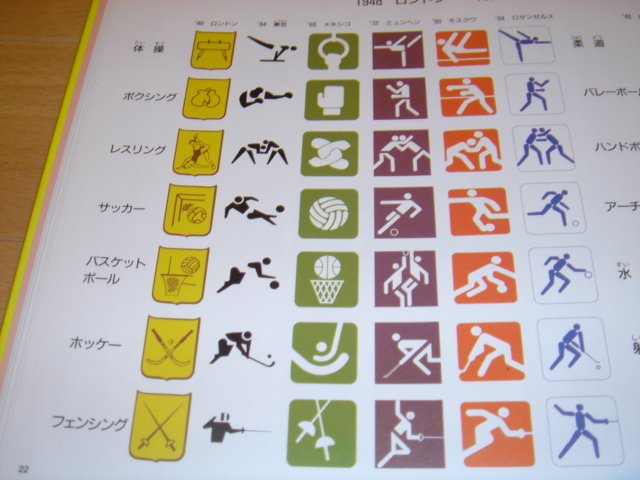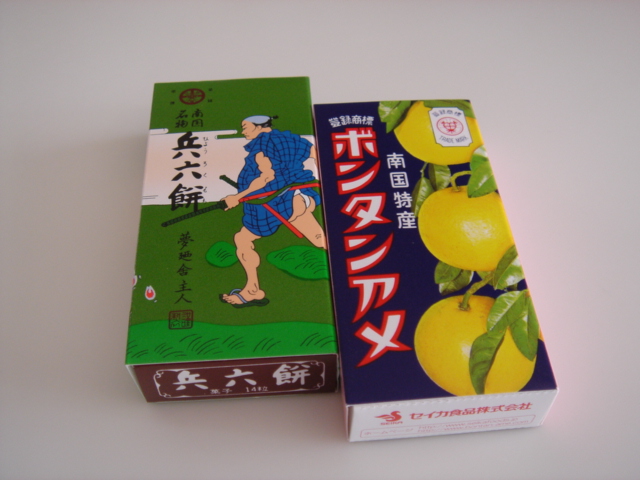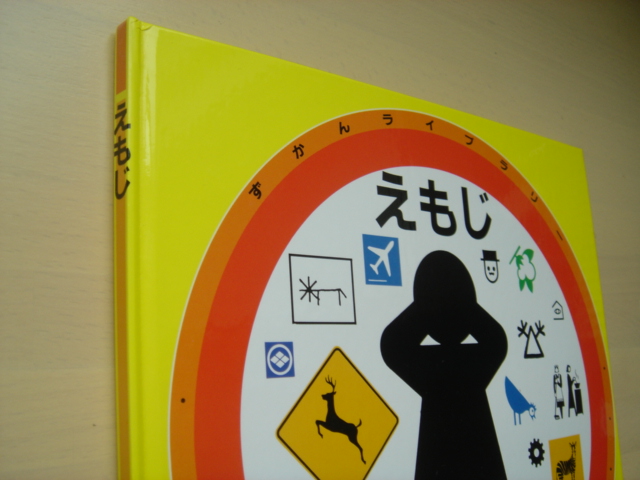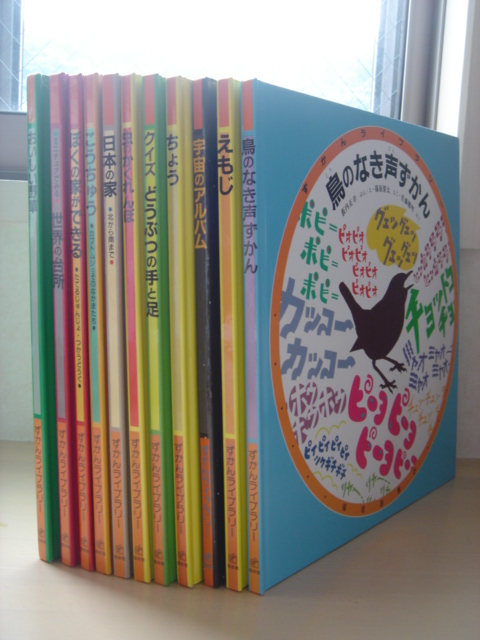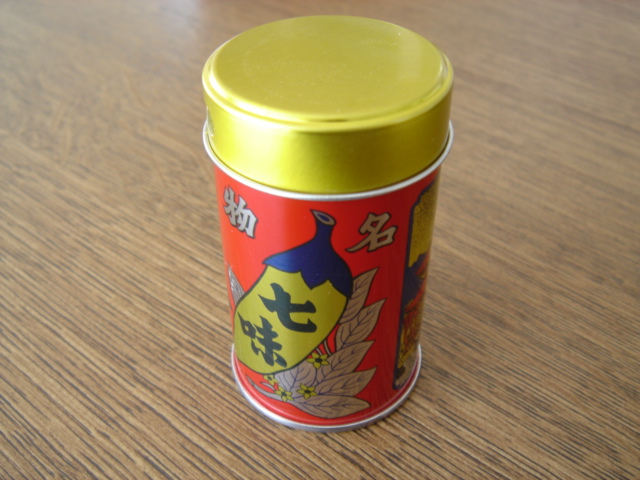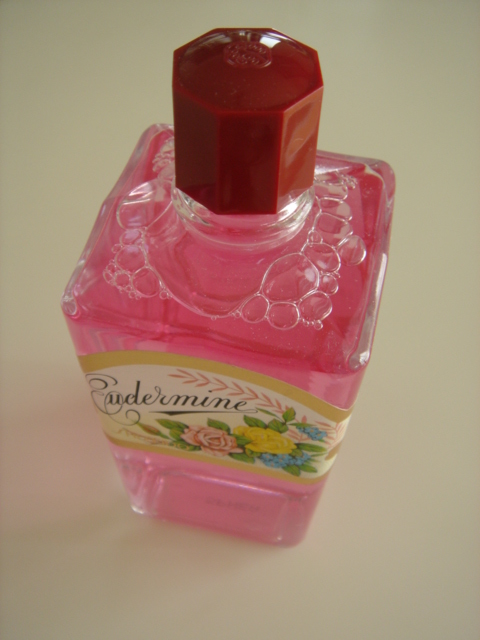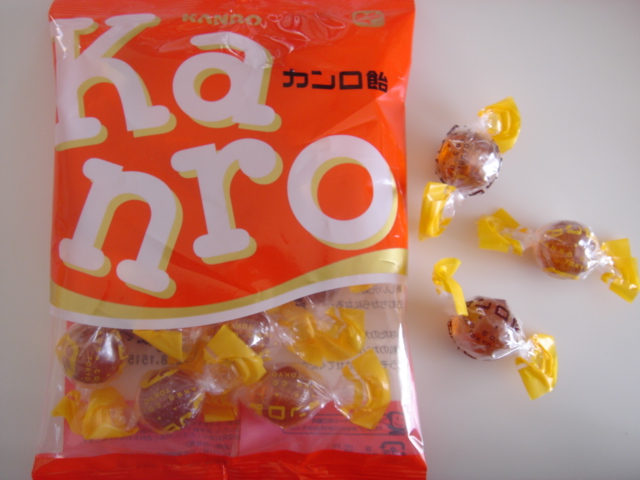
昔なつかしパッケージ
近所にドラッグストアがあるので、いざというとき便利です。
なぜかお菓子を買うことが多いですが…(どうでもいい「いざ」ですね)
先日ぶらぶらと棚を見ていたら、これを、発見!
なつかし〜。母の鏡台にあったわ〜。ピンク色の化粧水。
オイデルミン、ああ、そんな名前だったかも。
と、手にとったらかわいいラベルとレトロなビンの形に目がくぎづけ!
ところでこれ、なんですか?ははあ、ふき取り化粧水ですか。
もう、いかにも色つけました、というピンク色で、ああ〜かわいいっ!
昔から変らないものってなんてすてきなんでしょう。
置いておくだけでも幸せ感がたっぷりです。特にフタの形がいいです。
使ってみたところ、香りにビックリですが、使用感はなかなかよかったですよ。
お菓子も昔からあるものはパッケージも魅力的ですよね。
森永のキャラメルや明治のサイコロキャラメル、好きですねえ。
このボンタンアメは駅の売店などにもあるような…この箱も昔から
変らないですね。
左の兵六餅はご存知?
抹茶ふうな味の(食感はボンタンアメと同じ)素朴なお菓子です。
九州人はよく食べるのかなあ。子どものころからのおなじみの味です。
ミルク系の飴がのどにいい、と信じている私ですが
ここのところのメラミン騒ぎで、ちょっと敬遠しております。
スースーしないタイプで、のどによさそうな飴はないかしら?
すると目に付いたのが「カンロ飴」、まだあるんですね!
このねじってあるタイプの飴は最近見かけないですから貴重。
なつかしい味です。噛みにくいから長持ちしますね、変なところに感動。
これもお気に入り!
先週信州小旅行に行ったとき、お昼は二回ともお蕎麦屋さんへ。
どっちのお店にも置いてあったのがこの七味でした。
容器のデザインに惹かれて即買いです。
かわいいなあ。
食卓でもにんまりしてます。
えもじ
調べたいことがあって、ふと思い出した子ども用の図鑑です…
絵本のような図鑑のような、なかなかユニークなシリーズなので「あれは確か、あのページに載っていた」という記憶がはっきりしているのです。
福音館書店の「ずかんライブラリー」というものですが、書店での発売はなく幼稚園での注文販売でした。このシリーズの中に「えもじ」があります。パラパラ見ているだけで楽しい!
北京オリンピックのテレビ放送でいろいろな競技のピクトグラムを見るのはなかなか楽しかったです。パラリンピックも始まりますが同じ人がデザインしているのでしょうか。
スポーツなどの大会に限りませんが異なる言語の人々のためにシンプルに表現されているのは、本当に見事。
で、この「えもじ」の中にもオリンピック競技のものがありました。
1948年のロンドンオリンピックでは、ボールなど競技に使う物や道具をデザインしたものが多かったんですね。その後は「人」中心のデザインに変わっているんだ〜。
私は東京オリンピックの時のものが好き。とても洗練されていると思います。
8年後に東京でやるなら、またこれを採用するなんてことは…ないのかな。
街中や公共の施設では欠かせない絵文字。非常口のサインはやっぱり目立ちますねえ。一番お世話になっているのはやっぱりトイレ…?
男女を青と赤で区別しているのは日本や韓国だけのようなのですが、これに慣れているせいか、たまに男女とも黒で(オシャレに!)表示されていたりすると「あれ、どっちかな?」とまじまじと見てしまいます。
先日出かけたレストランでのできごと。
うちの小学生(男子)が「男のトイレがない」と席に戻ってきました。「どうしよう!」と焦っているので、一緒に行ってみると
確かに女子トイレのサインはついているけれど、男子のほうはプレートがはがれてしまったのかドアに何も表示がありません。
「片方が女子用なのだから、このドアのほうで大丈夫」と言うと「ほんとにだいじょうぶ?」とおそるおそるドアを開けていました。
自信を持って行動するためにも絵文字は大事で〜す。
美篶堂のbookstand
前に美篶堂さんでゲットしたbookstandで、一度ご紹介は
したのです…。
でもそのときは地面に立てて…。
しかし、このbookstandは、壁面にも掛けられる
優れものです。
壁にピンをで二か所とめて、そこにチェーンを
掛けます。
ちょっと恐かったら、両面テープを少し貼っても…。
姿がいいですよねぇ〜。
受け板部分が少し斜めになっているので、
カードを立てても落ちたりしません。
姿がいいでしょう〜。
ある程度の重いものも、大丈夫みたいです。
これなら文庫本とか小さなノートとか
フレーム入りの写真とか飾れます。
美篶堂の提供するもの、空間は、私の憧れです。
もう一個買おうかなぁ〜。
アルファベットのハンカチーフ
おしゃれな人からの贈り物…刺繍の美しいハンカチです。
とっても薄い綿ローン地に繊細な手刺繍で、葉っぱのところは裏側に糸がわたっているので表面はぷっくりと見える…アップリケをしたみたいな。
一枚の布として見ても、ハンカチって魅力的ですよね。
最近こんな優美なハンカチを使うことが少なくなりました。手を拭くのにはタオル素材のハンカチを使っているためです。
タオルハンカチはそれなりにかわいく、しかも実用的。だけど、日々美しいものを身の回りに置いて、見たり、使ったりも大事ですよねえ。
涙をそっと押さえたり、とか?美女なら持っているだけで
絵になります。
さて、文字入りのハンカチは引き出しにあったはず…ありました〜
華やか!周囲全部ローマンキャピタルですから!プロポーションをしっかりお勉強、って感じですかね。
パロマ・ピカソの名前入ってる…あ、だから四隅は「P」なのね。
中央の地模様も全部アルファベット。ごちそうさま〜
こういうハンカチってデザイナー本人がデザインしているのでしょうか?
絹と綿が半々のスベスベの手ざわり。周りの切り文字っぽいデザインがおもしろい。
中央部分の字はあまり好きではないけれど…「KとL」が金色になっているのは、カール・ラガーフェルドだから、か。イニシャルが隣り同士というのは、こんなふうに遊べるのですね、いいなあ。
久しぶりに出してみて思ったこと。もったいなくて使えない、よりも使って楽しいほうがいいかも。
粋な手拭い
今や手拭い専門店もある今日
この頃。
軽くてコンパクトで…。
今回は、また面白いデザインを見つけました。そのタイトルも「NIPPON」とな。
シンプルな図案がいいですね。見ながら説明できたら話しも盛り上がることでしょう〜。
でもTEMPURAはツェッペリンに見えなくないかも?
こちらは「手影絵手本」とな。
ぁあ〜、懐かしい!
子供の頃は遊びましたねぇ〜。
おばあちゃんに教えてもらいました。幼稚園でもやったような…。
海外では、どんな手影絵があるのでしょうねぇ〜?
鳴き声の違いとかすると面白いかもしれませんね…。
太陽の光が透明で強い1月あたりが撮影には
良いかと…。
風と戦いながら〜。
貼りまぜ屏風
昨年の夏の話です。
九州のとある民家に泊めてもらった日、そこの女主人にその家の家宝を見せてもらいました。貼り交ぜ屏風1双です。
貼り交ぜ屏風とは、色紙・短冊・書簡等をとりまぜて屏風に貼りあわせたものです。たくさんの書画を貼り合わせて作った華やかなふすまや屏風のことで、その貼る位置は屏風を作る表具師
のセンスによってレイアウトされます。
この屏風は女主人が、以前ある骨董屋さんで出会って一目で気に入り、清水の舞台から飛び降りる決意で購入したのだそうです。やったね〜!
一つ一つが本当に面白いので、ながめていて飽きません。長い時間をかけてゆっくり鑑賞させてもらいました。素晴らしい時間でした。
その貼りまぜの中にこんなのもあったのです。
蛇口の鳥亀?
これを屏風に貼っちまえ、と思ったこの所有者。いいぞ!このセンス。そしてちゃんと上下たてよこ間違わずに貼った表具師さんもエライ!
九州前原にある、かの銀河荘に行って女主人にお願いすると見せてもらえるかもしれませんよ〜。
カレンダーもうひとつ
今年もあと2日で終了。一夜飾りにならない様にとお供えやお花など飾るものは今日やらないとね。
ということで、仕事場のカレンダーも新しい物と取り替えます。
昨年とても使いやすかったほぼ日ホワイトカレンダー
今年はタカモリ・トモコさんの編みぐるみのデザインです。
来年はねずみ年だからまず1月にはねずみちゃんが登場。どの後はいろいろな動物が出て来ます。
所々の日にちの数字が、編みぐるみによってかじられたり、持って行ってしまったり、楽しい展開です。
このほぼ日の壁掛けホワイトカレンダーには、ホワイトボードマーカーが3色ついていて、書いては消し、消しては書くができるので、とても便利なのです。ホワイトボードなのにカレンダー。しかもデザインがかわいいので、たぶん人気があるのでしょう、今年も売り切れとなってるようです。
みなさま、大掃除や年賀状書きは終わりましたか? 終わった人も終わらない人も、やっぱり夜はみかん食べながらゆっくりと今年一年を振り返って、反省とそして来年へ向けての豊富を考えましょうね。
さて、明日で今年もおしまいです。
2008年の真っ白なカレンダーが幸せで一杯になりますように。
マンゴーがトロリ甘いので、青汁が引き締め役で、とても美味しかったです!意外!
その友人にあのエルメスのビルに案内してもらい・・・別に買い物じゃあないんです(汗)
ギャラリーで展示をしてるのが結構面白いらしく、それを見ようと思ったら、ちょうど入替えで
やっていませんでした。
でもそれとは別にエルメスの作品を展示しているギャラリーもあるんですね・・・。
それを知らずに・・・その階に降りてしまい、係りの方がとても親切で、「いつもはご予約が必要
なのですが、今はお客様がいらっしゃいませんので、もしよろしけれなどーぞ。」とな・・・。
エルメスのことは全くわからないけど、面白そうだから入ってみよう〜と好奇心!
一番驚いたのは、ギャラリーの中が真っ白なので、色が目に入ると邪魔らしく、白衣を
提供されました。袖を通してお互いの背中に・・・あのエルメスのデザインが・・・後光がさして
おりました・・・拝みましょう〜。
きっとエルメスのものにはご縁がないと思われますので、唯一エルメスを試着したことになるの
ですね・・・ホホホ。一番目に留まった展示は、何か革が層になっているバッグでした。
二人で「何かに似ている・・・ぉお〜キムカツか・・・」